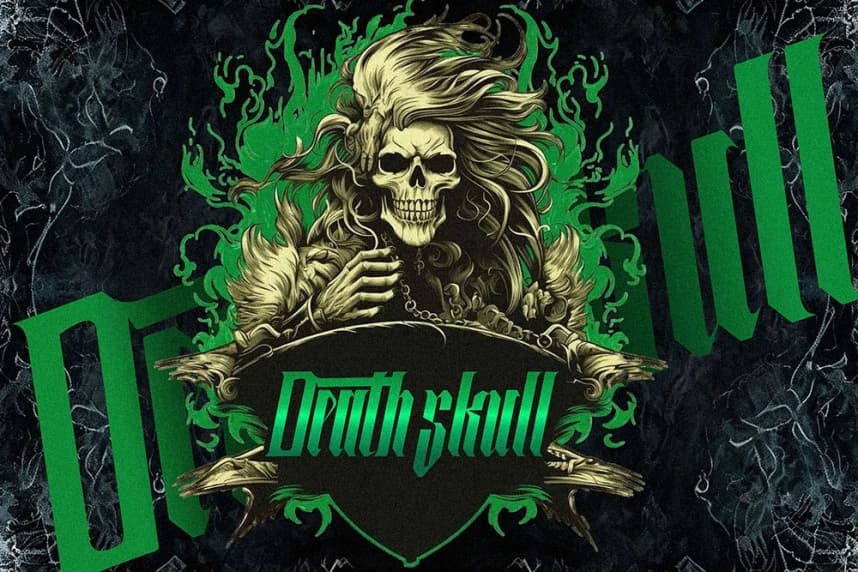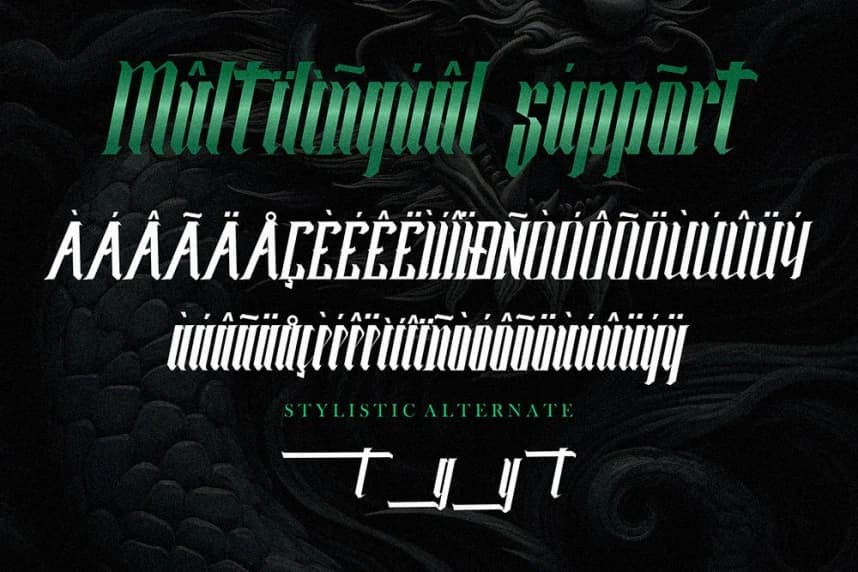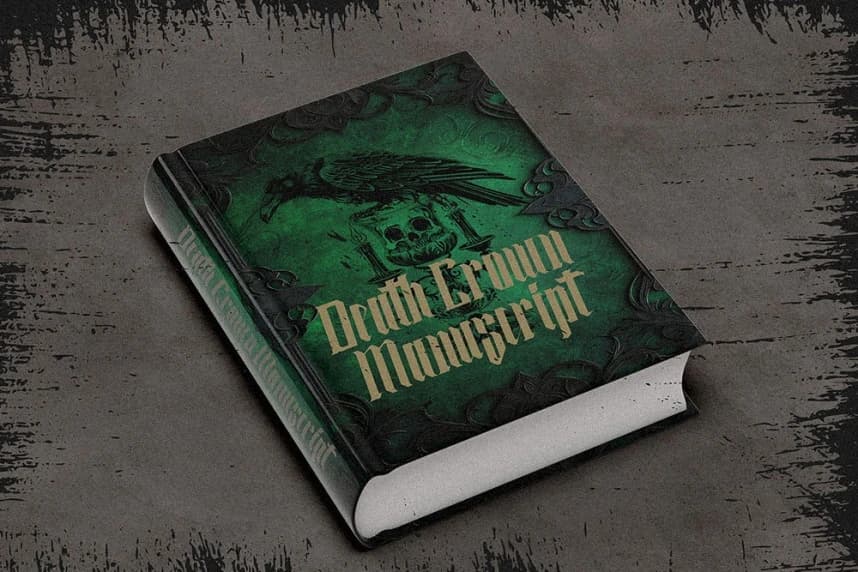
Silent Blade Font
Silent Blade Font – Modern Blackletter Font, Cesur Gotik Tasarım için. Tipografi, kimlik, duygu ve unutulmaz izler yaratma gücüne sahiptir. Silent Blade – Modern Blackletter Font, gelenek ile modern cesareti bir araya getirmek isteyen tasarımcılar için tasarlanmıştır.
Silent Blade Font – Modern Blackletter Font Kalın Gotik Tasarım için. Tipografi, kimlik, duygu ve unutulmaz izler yaratma gücüne sahiptir. Silent Blade – Modern Blackletter Font gelenek ile modern cesurluğu bir araya getirmek isteyen tasarımcılar için tasarlanmıştır.